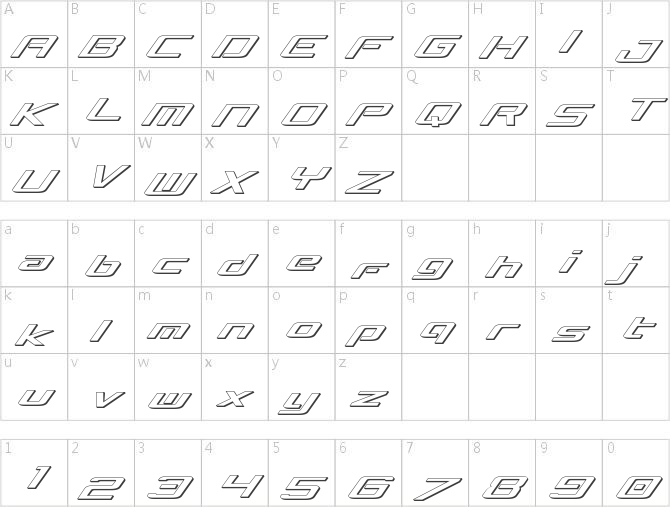
Concielian Break 3D Italic 詳情頁
Concielian Break 3D Italic字體字庫是一款讓人賞心悅目、百看不厭的英文字體,適合各類廣告和產(chǎn)品包裝設(shè)計(jì)應(yīng)用,字體大小0.05MB,格式為ttf字體,上傳用戶是那是不變的,作者/版權(quán)方為未知